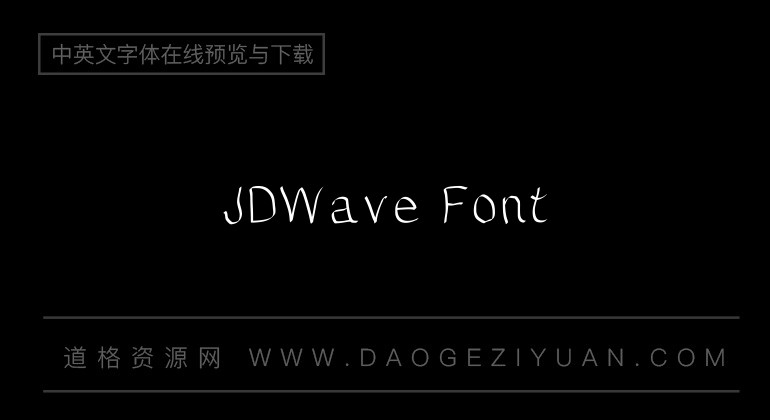
JDWave Font 是一款英文字体,其特点是每个字母都呈现出波浪形状,让人感觉非常独特和有趣。这种字体适用于需要独特和有趣设计的场合,比如海报、广告、品牌标识等。 JDWave Font 字体的设计师是日本设计师 "Jidan",他的设计理念源自于海洋和水的自然形态,他希望将水的流动感和波浪形状融入到字体设计中,从而创造出一种独特的视觉效果。 JDWave Font 字体可以免费下载使用,支持 Windows 和 Mac 操作系统,同时也提供了多种字体格式,包括 TrueType、OpenType、WOFF 等。内容介绍
JDWave Font是一款非常不错的手写艺术字体,具有很好的视觉感,适合于文化类的宣传设计、商业类品牌的广告和产品包装设计以及个性化文字排版等较多场景。